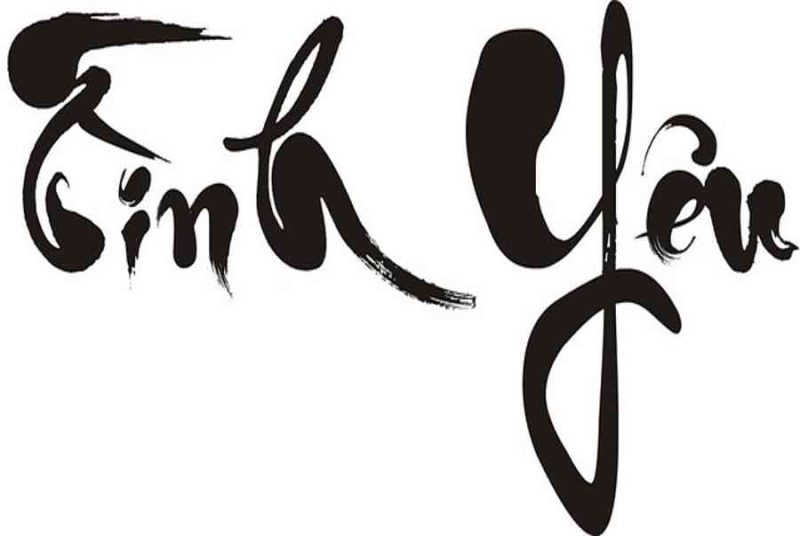
Font chữ thư pháp việt hóa được sử dụng trong các thiệp mừng, thiệp mới, thiệp cưới, hoặc các bảng hiệu quảng cáo. Qua đó làm nổi bật lên những gì mà bạn muốn đề cập tới người xem. Phông chữ thư pháp đẹp phù hợp. Sẽ có thể cải thiện ngay lập tức giao diện của bản trình bày tiếp thị của bạn. Gây ấn tượng với khách hàng hoặc nâng cấp thiết kế của bạn từ trung bình lên đặc biệt. Nhưng thường rất khó để tìm được một phông chữ nằm ở khoảng giữa sang trọng và ấn tượng. Đặc biệt là khi bạn không sẵn sàng trả tiền cho một nhà thư pháp có kinh nghiệm.
Font Thư pháp là gì?
Phông chữ thư pháp có tính nghệ thuật hơn phông chữ trung bình, thường sử dụng kiểu chữ viết để mô phỏng giao diện của chữ viết tay. Nhưng nghe có vẻ chung chung, có hàng tá phong cách thư pháp mà bạn có thể lựa chọn.
Có ba loại thư pháp chính : phương Tây, phương Đông và Ả Rập. Mỗi loại phản ánh ngôn từ và chữ viết tay của một khu vực khác nhau trên quốc tế. Trong khi thư pháp phương Tây biểu lộ chữ viết tay bằng tiếng Anh, thì thư pháp phương đông gồm có hầu hết những bảng vần âm châu Á. Thư pháp Ả Rập là một kiểu chữ cao dựa trọn vẹn vào bảng vần âm Ả Rập .
Tại sao nên sử dụng Font chữ thư pháp Việt Hóa
Font chữ thư pháp Việt hóa thường được sử dụng cho những tiêu đề ngắn và làm trọng âm. Vì chúng thường trở nên khó đọc. Nếu chúng được sử dụng trong những chuỗi văn bản dài hơn. Điều đó có nghĩa là bạn hoàn toàn có thể muốn tìm cho họ một đối tác chiến lược đơn thuần. Giống như Abbott so với bức thư pháp Costello của bạn. Taingay đã tổng hợp 1 số ít font thư pháp đẹp để những bạn thuận tiện sử dụng không tính tiền. Cách tích hợp để khởi đầu và bạn hoàn toàn có thể tìm hiểu và khám phá thêm về cách chọn và trộn trong bài viết ghép nối font chữ .
Các kiểu font chữ thư pháp Việt hóa
Hiện tại, Font thư pháp phân phối hàng chục kiểu font chữ độc lạ cho người dùng lựa chọn. Một list những phông chữ đẹp sẽ hiện ra và bạn chỉ cần vận dụng. Bất kỳ kiểu chữ nào cho những tài liệu đã chuẩn bị sẵn sàng đều hoàn toàn có thể biến chúng thành những định dạng phông chữ mới và độc lạ. Ngay lập tức với nhiều nét vẽ khác nhau. Giúp bạn viết văn bản theo nhiều kiểu trên nhiều hình ảnh, không bị trùng lặp. Do đó, hãy sử dụng font chữ này để :
- Thiết kế hình ảnh
- Thiệp Bìa sách
- Vở sách,…
Chắc chắn sẽ mang lại hiệu suất cao tích cực .
Ưu điểm của font chữ thư pháp Việt hóa
Dưới đây là một số ít tính năng điển hình nổi bật của font chữ thư pháp. Được Taingay tổng hợp từ nhiều nguồn trên Internet. Về cho đồng đội sử dụng không lấy phí, kỳ vọng những bạn hoàn toàn có thể vận dụng vào việc làm thuận tiện. Hãy tìm hiểu thêm một số ít ưu điểm của font chữ thư pháp Việt Hóa .
Font chữ thư pháp hỗ trợ thiết kế
Font chữ thư pháp được hỗ trợ trên hầu hết các phần mềm chỉnh sửa ảnh. Thế nên việc sử dụng font chữ thư pháp Việt Hóa trong thiết kế đồ họa là điều cần thiết. Với Font thư pháp, bạn sẽ trở thành một chuyên gia thực thụ. Sử dụng font chữ thư pháp trên các phần mềm chỉnh sửa ảnh như Photoshop, Paint … giúp bạn tạo ra nhiều đường nét, câu đố có đường lượn sóng đẹp nhất để chia sẻ lên các mạng xã hội hiện nay như Facebook hay Zalo … Mã nguồn là tài sản quý của chúng ta dân tộc được lưu truyền qua nhiều thế hệ. Với công cụ này, người dùng có thể ghi nhớ và lưu giữ tài sản đó, tạo chữ thư pháp để làm tranh hoặc tặng bạn bè vào các dịp lễ, tết.
Font chữ thư pháp dễ dàng thích ứng với bộ gõ Tiếng Việt
Font thư pháp hay còn gọi là font ông đồ là loại font có nét chấm phá, cho bạn tạo ra những tác phẩm nghệ thuật và thẩm mỹ độc lạ. Đây là font True Type, được đánh theo mã VNI, thuận tiện thích hợp với những bộ ngôn từ tiếng Việt trên mạng lưới hệ thống. Dưới đây là hàng trăm phông chữ độc lạ cho bạn lựa chọn. Các bộ Font Thư Pháp nổi tiếng như Font Thư Pháp Thiên Ân, Font Thư Pháp Công Thủy hay Font Thư Pháp Thành Công đều có tính thích hợp cao, bạn hoàn toàn có thể tìm hiểu thêm .
Kiểu chữ thư pháp việt hóa thường gồm có hai loại dưới đây
- Văn bản.
- Tranh chữ (thư hoạ).
Văn bản hoàn toàn có thể là một tập thơ, bằng khen hoặc là một thiệp mời đám cưới. Tranh chữ thì hoàn toàn có thể là một từ chủ yếu hay một tập hợp được trình diễn trong một khuôn hình nhất định .
Font chữ thư pháp đẹp
Font thư pháp đẹp
Phông chữ thư pháp 2021
Hướng dẫn cách viết chữ thư pháp, font chữ ông đồ
Sử dụng font chữ thư pháp để viết thư pháp trên photoshop hay những ứng dụng chỉnh sửa ảnh khác không phải bạn nào cũng làm được, hãy tìm hiểu thêm cách viết thư pháp, tạo chữ thư pháp trên máy tính để viết câu thơ. Ca Dao, tục ngữ bằng chữ viết cổ của thư Pháp. Thay vì tải những bộ font riêng không liên quan gì đến nhau trên máy tính, bạn hãy sử dụng trọn bộ Font được phân phối trên taimienphi với nhiều font cơ bản để gõ tiếng Việt trên máy tính như chat, soạn thảo văn bản, Font. full tích hợp nhiều font chữ khác nhau cho cả phong cách thiết kế và vẽ mỹ thuật .